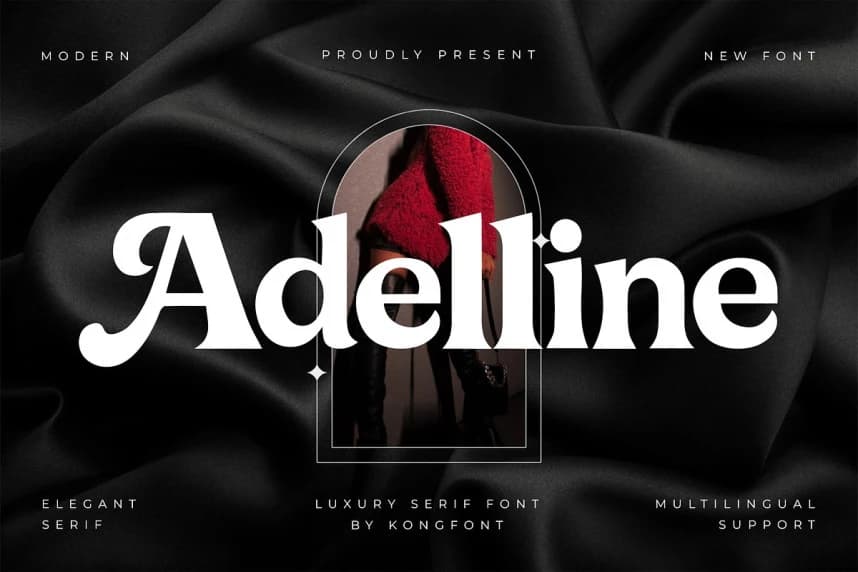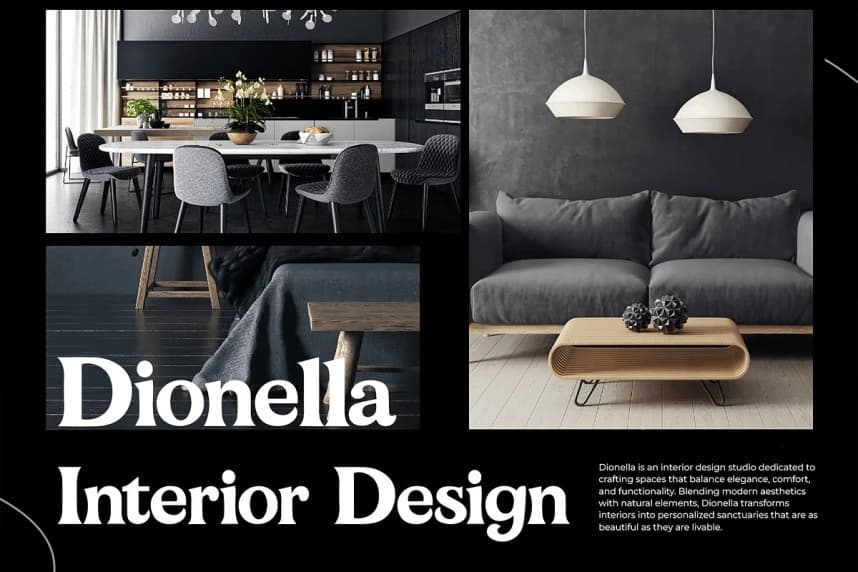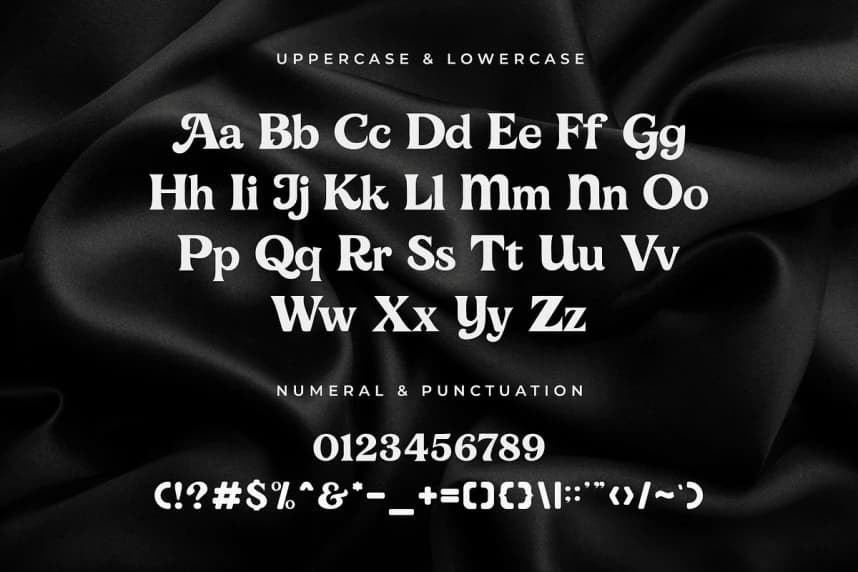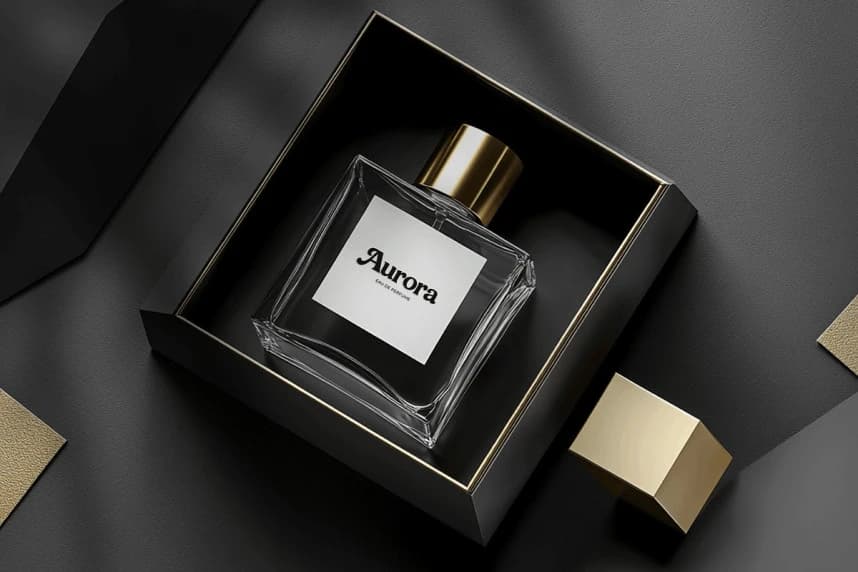
Adelline Font
Adelline Font, zamansız zarafet ve sofistikasyonu yansıtan lüks bir serif fontudur. Güzel eğriler, yüksek kontrastlı hatlar ve klasik oranlarla tasarlanan Adelline, üst düzey markalaşma ve editoryal düzenlerden düğün davetiyelerine ve lüks ambalaja kadar her tasarım projesine premium bir hava katar.
Adelline Font, zamansız zarafet ve sofistikasyonu yansıtan lüks bir serif fontudur. Zarif eğriler, yüksek kontrastlı hatlar ve klasik oranlarla tasarlanmıştır; Adelline, üst düzey marka tasarımı ve editöryal düzenlerden düğün davetiyelerine ve lüks ambalaja kadar her tasarım projesine premium bir his kazandırır.